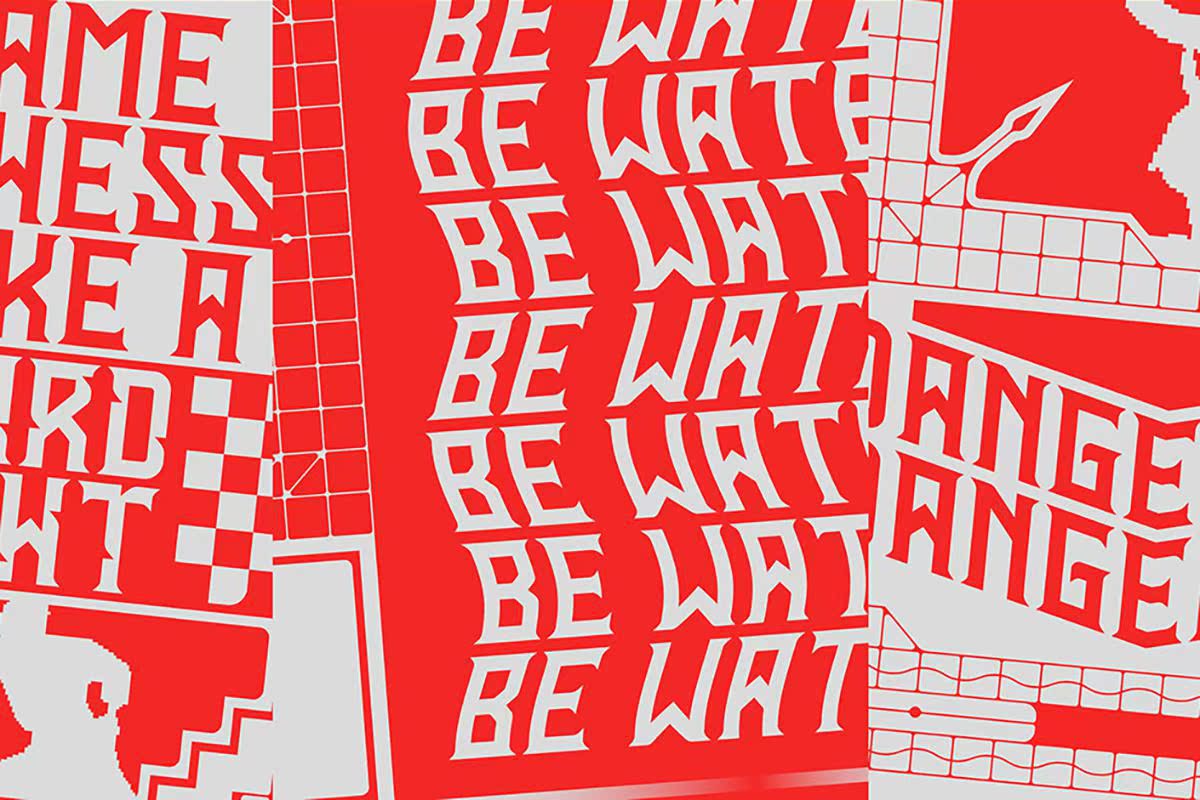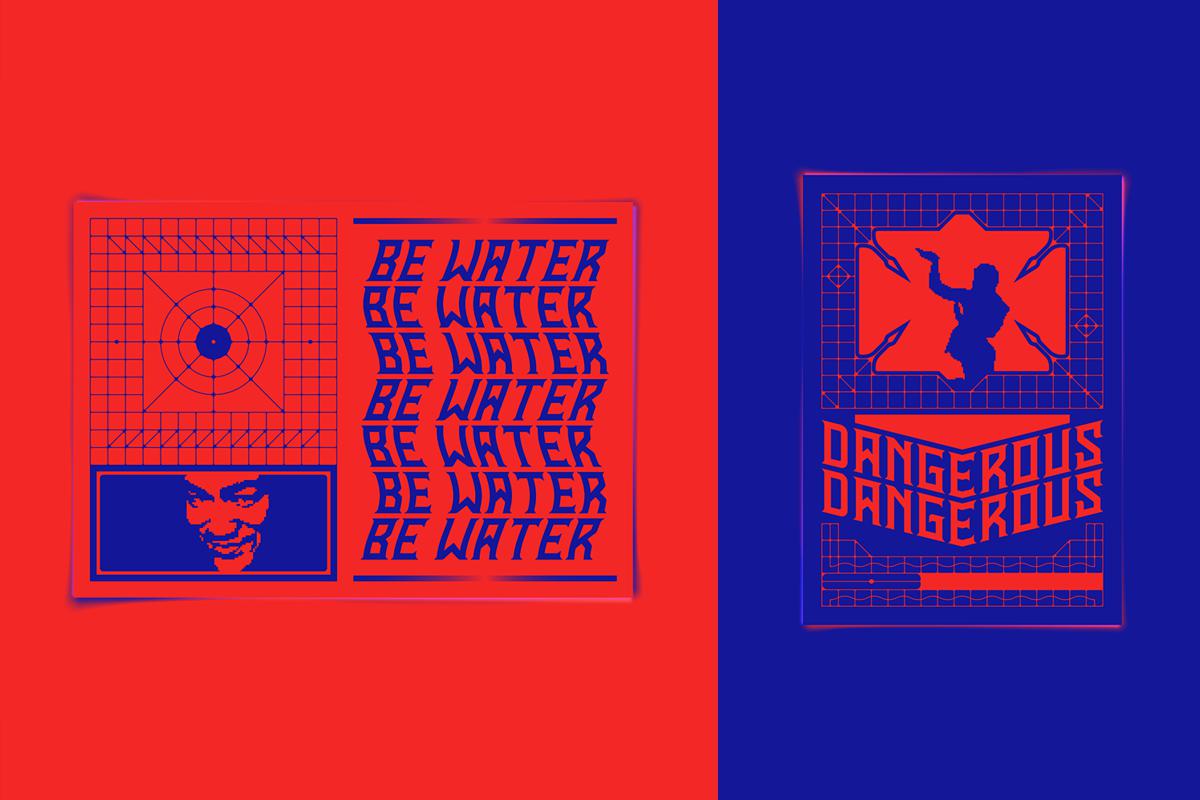
Enguard Afree Display Font是一种现代化的字体,它与西方的防腐蚀设计和排版技术相适应,同时也是一种现代化的字体。它采用了先进的工具、精选的材料、艺术和游戏,让玩家能够在游戏中畅游。SnakeintheEagle’sShadow.Vertical Kombat和InternalChampions。它是在当前关注的所有问题的情况下建立的t创建具有一致性和可读性的HarmonicResults。